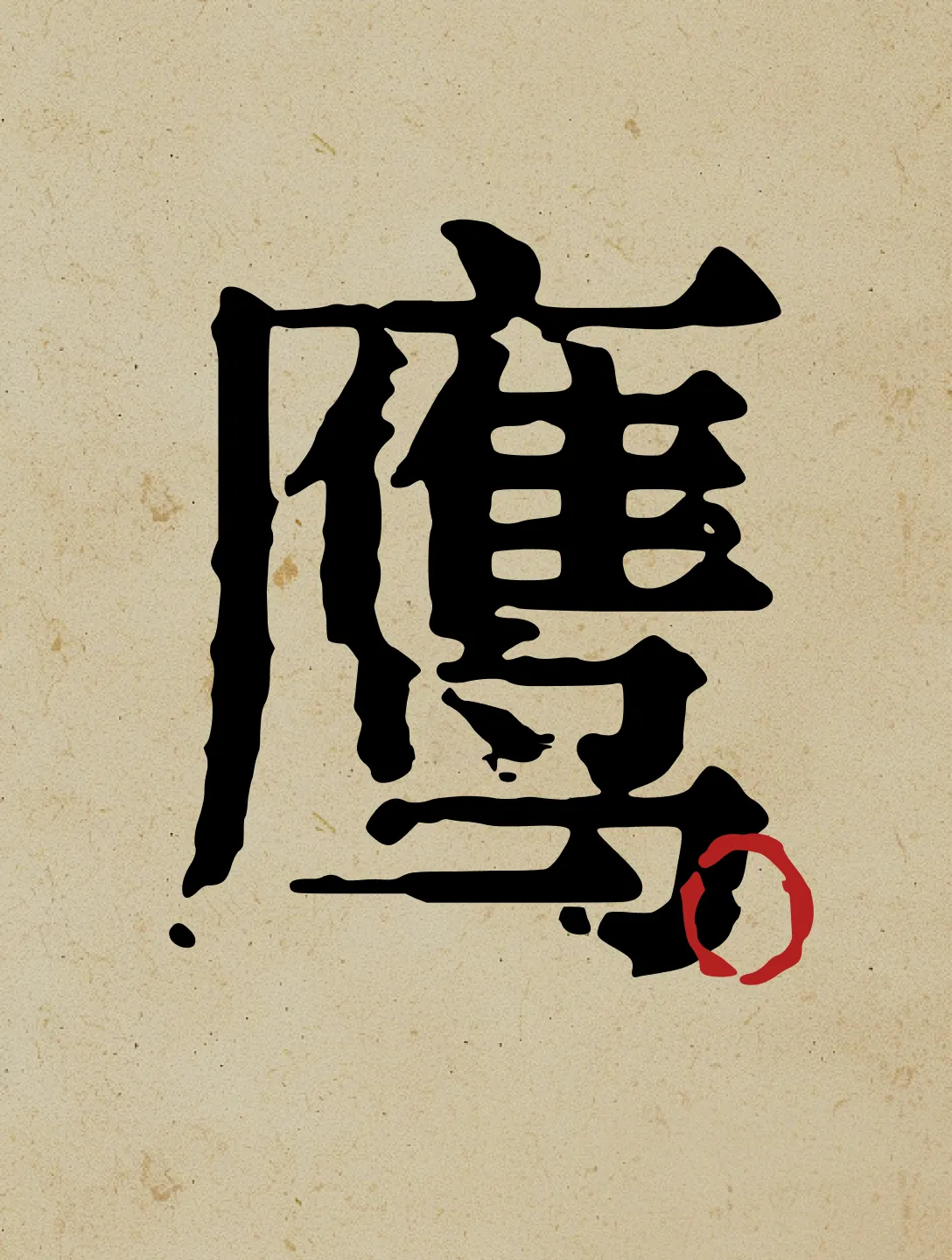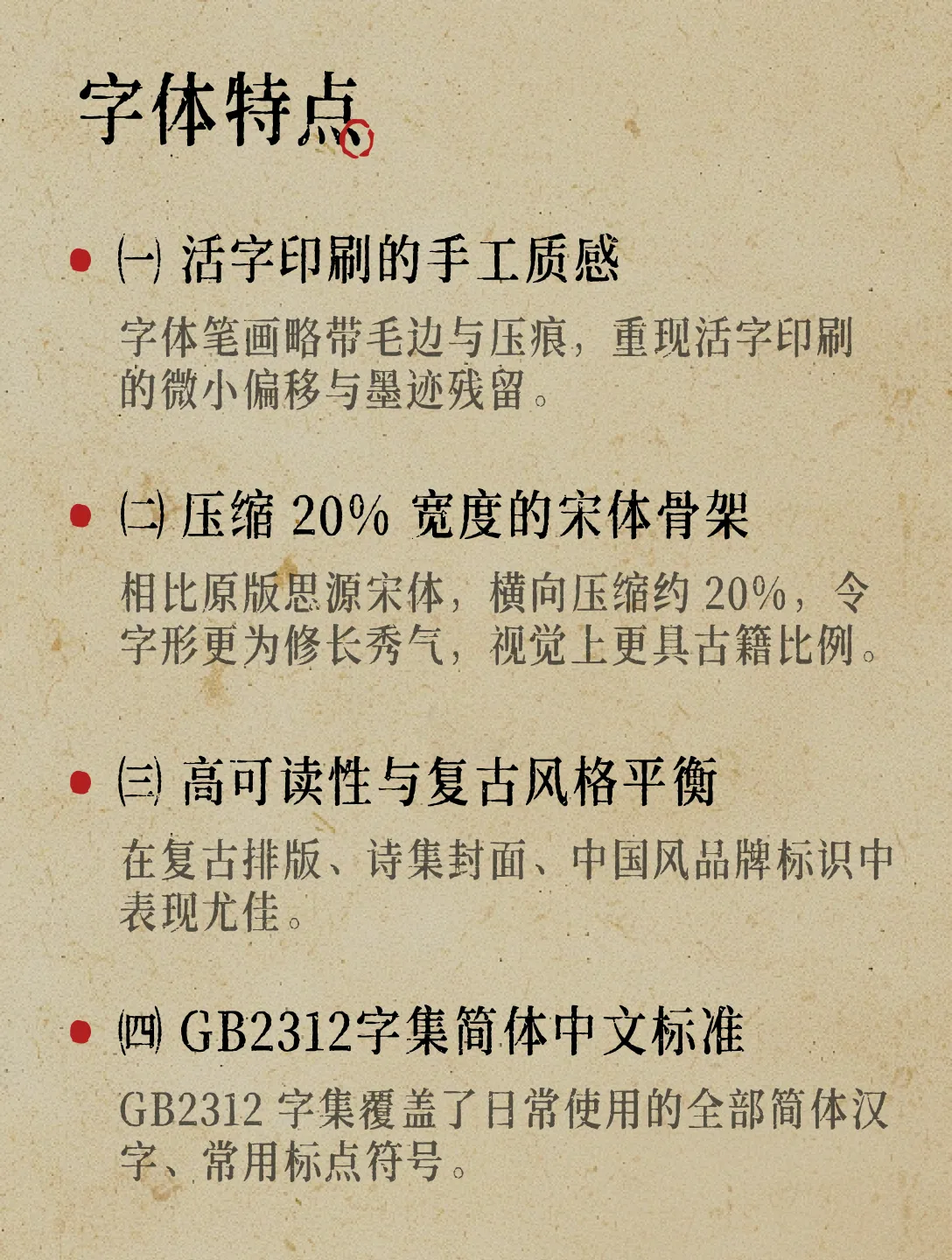
思印宋
思印宋,这款字体结构工整、笔画清晰,兼顾美观与易读性,适用于标题、正文、海报、包装、LOGO 等多种场景。字形优雅稳定,风格百搭耐看,适配日常排版与创意设计,让文字呈现更舒适、更具质感。思印宋一笔一画,皆是细节,以均衡的比例、流畅的线条打造舒适视觉体验,字形端正大气,风格简约现代。无论是商业设计、品牌宣传还是日常排版,都能轻松驾驭,让文字更有格调与力量。思印宋字体下载。
字体名称:思印宋(Si Yin Song)
英文名称:SiyinSong
字集范围:GB2312
母版来源:思源宋体(Source Han Serif)
㈠ 活字印刷的手工质感
字体笔画略带毛边与压痕,重现活字印刷的微小偏移与墨迹残留。
㈡ 压缩 20% 宽度的宋体骨架
相比原版思源宋体,横向压缩约 20%,令字形更为修长秀气,视觉上更具古籍比例。
㈢ 高可读性与复古风格平衡
在复古排版、诗集封面、中国风品牌标识中表现尤佳。
㈣ GB2312字集简体中文标准
GB2312 字集覆盖了日常使用的全部简体汉字、常用标点符号。
字体介绍:
《思印宋》是一款基于思源宋体设计的无衬线字体,具有轻微的毛边和压痕效果,模拟活字印刷的质感。字形横向压缩约20%,更修长秀气,同时保持高可读性。该字体支持GB2312字集,涵盖简体中文和常用标点符号,适合复古风格的排版、诗集封面和中国风品牌标识。
适用范围:
复古排版、诗集封面、中国风品牌标识,适用于印刷和数字媒体。